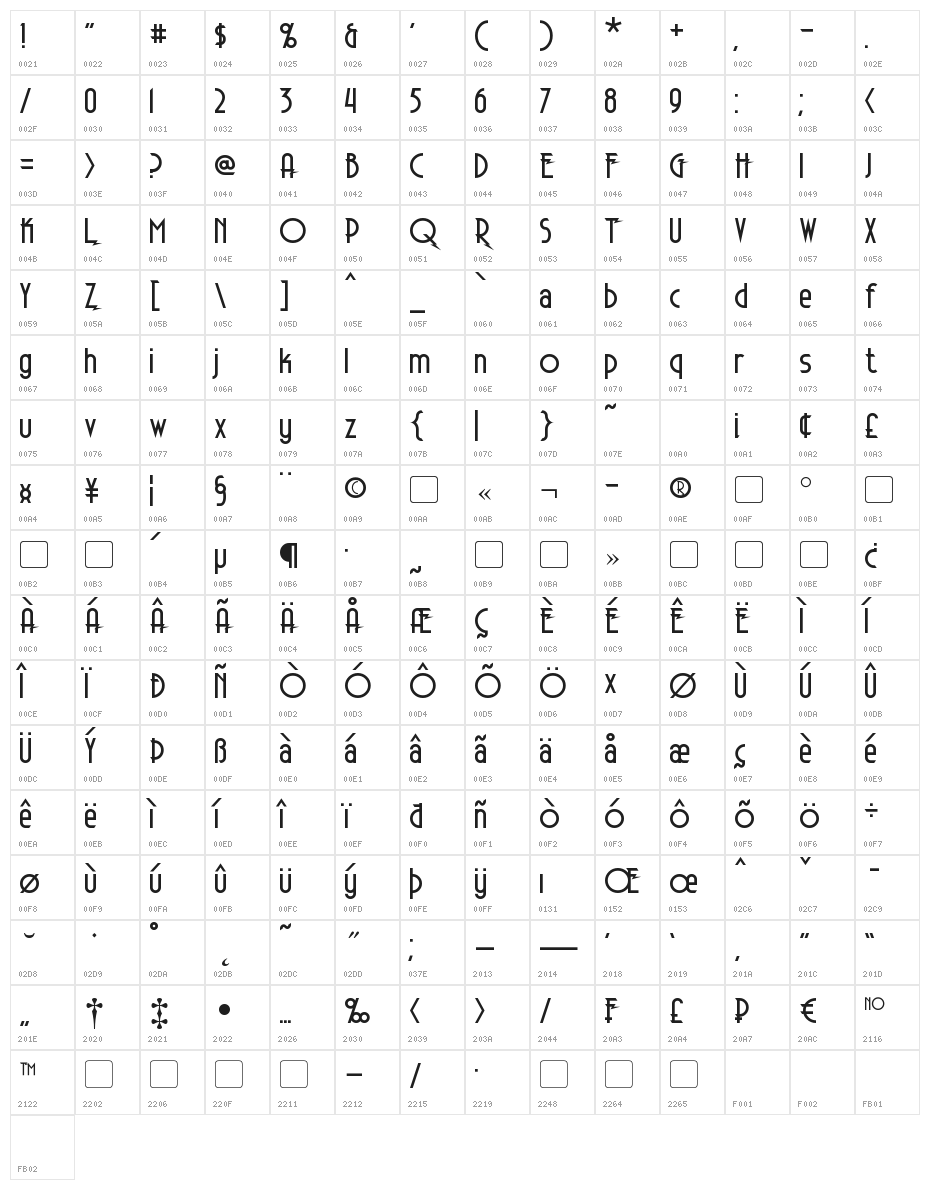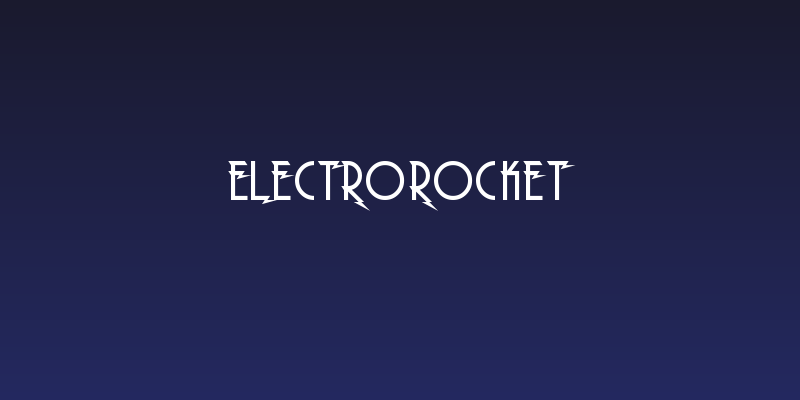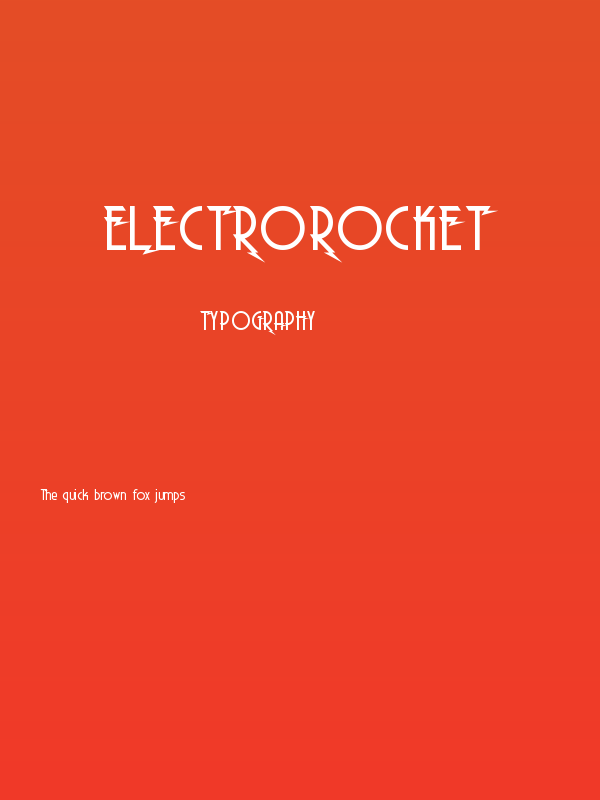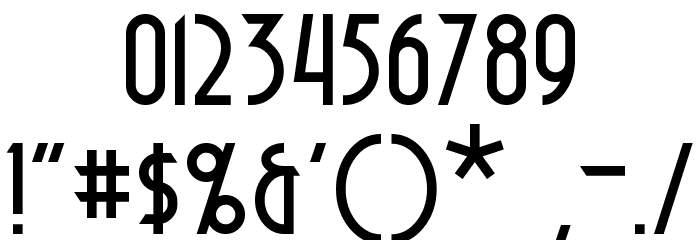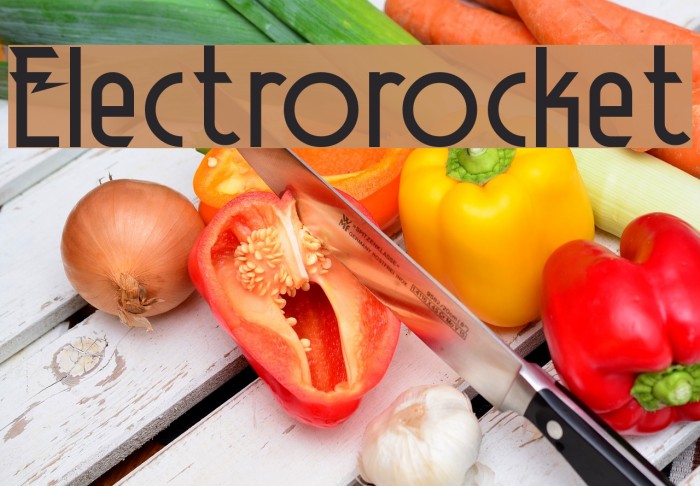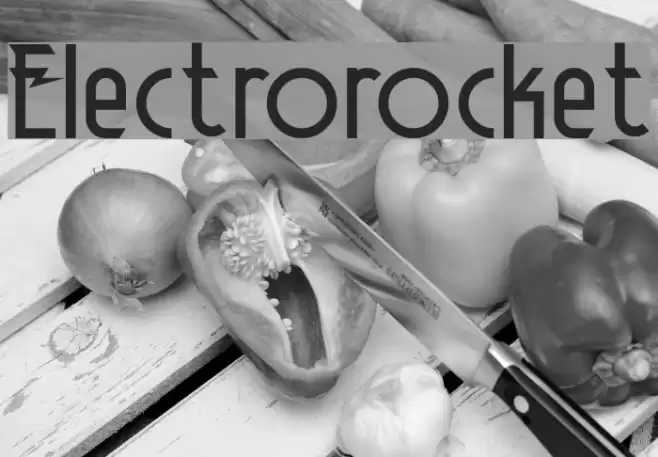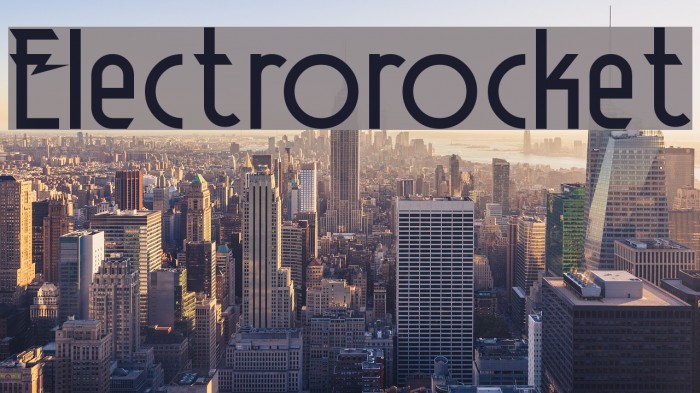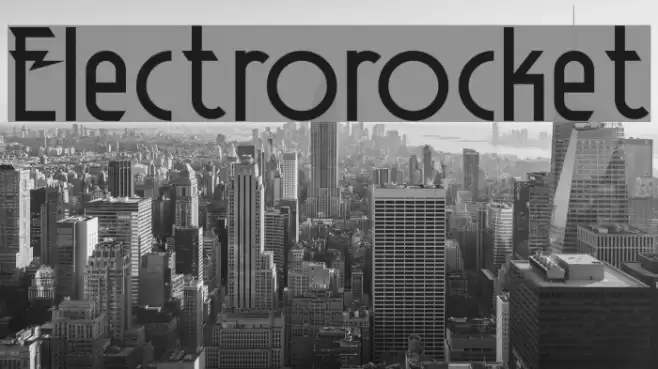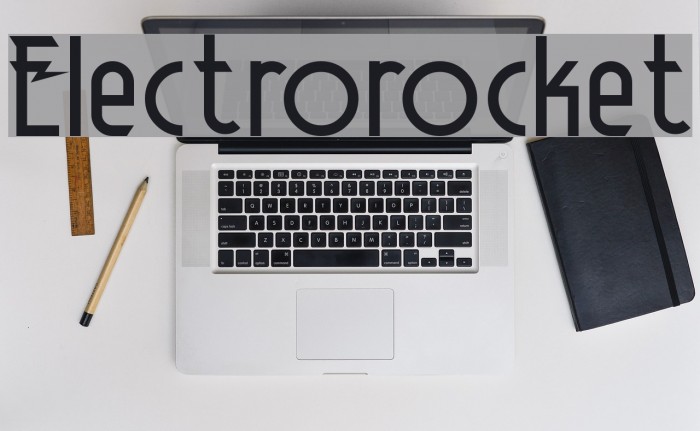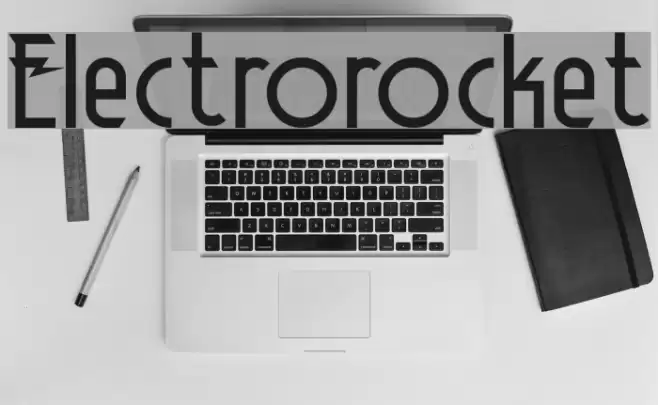
Electrorocket Font
| مشاريع مقترحة | Ideal for music album covers, event posters, branding for tech companies, and any project needing a bold, energetic look. |